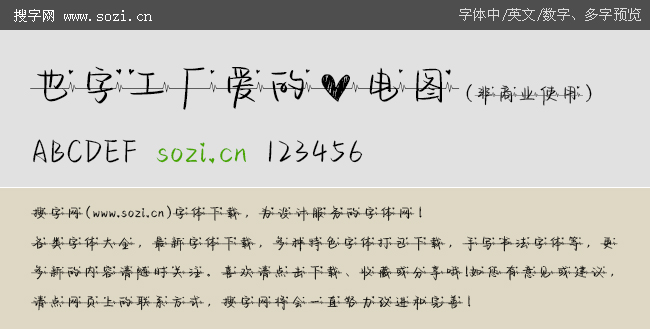
也字工廠愛的心電圖
搜字網(wǎng)給大家提供一款也字工廠愛的心電圖(非商業(yè)使用)中文字體下載,也字工廠愛的心電圖是一款卡通字體,字體為手寫風(fēng)格的書法字體,裝飾有心電圖圖案,并點(diǎn)綴了可愛的心形圖案,看上去趣味十足,適合應(yīng)用于藝術(shù)設(shè)計(jì)、平面宣傳設(shè)計(jì)、網(wǎng)頁(yè)設(shè)計(jì)、兒童海報(bào)設(shè)計(jì)等應(yīng)用(此字體為個(gè)人非商用版,商用可以聯(lián)系:官方網(wǎng)址:https://yefont.com/home,聯(lián)系方式:13798980448)。